Dla osób rozpoczynających naukę hand letteringu ważne jest, aby zacząć od podstaw i stopniowo rozwijać swoje umiejętności. Pamiętaj, że lettering to umiejętność, którą rozwija się stopniowo. Nie zrażaj się na początku, a z czasem zobaczysz postępy w swoich umiejętnościach letteringowych. W dzisiejszym artykule przedstawiam kilka wskazówek na start.
Narzędzia do Hand letteringu- od czego zacząć
Prawidłowa postawa ciała i ręki
To pewnie banalne, co napiszę, ale rysując litery metodami hand letteringu musisz siedzieć przy biurku. Na wygodnym krześle i przy biurku ustawionym na odpowiednią wysokość. Prawidłowa i wygodna postawa ciała pomoże w lepszym kontrolowaniu ruchów i uzyskiwaniu bardziej precyzyjnych linii podczas tworzenia napisów.
Zacznij od prostych krojów pisma
Hand lettering jest przepiękny, litery są fikuśne i często bardzo kreatywne. Jednak gdy jesteś na samym początku nauki, zacznij od prostych krojów. Napisz jedno słowo drukowanymi literami, następnie pogrub linie. W kolejnych krokach dodaj szeryfy. To pierwszy krok do kreowania pięknych liter.
Regularne ćwiczenia
Regularna praktyka jest kluczowa w rozwoju umiejętności letteringowych. Zarezerwuj czas w ciągu tygodnia na krótkie sesje praktyki, aby stopniowo doskonalić swoje umiejętności. Jeśli brakuje ci motywacji, zapisz się na warsztaty w swoim mieście lub zakup sobie kurs online, z którym będziesz regularnie pracować.
Naśladuj innych
Znalazłaś w sieci piękną grafikę? Zapisz ją sobie i spróbuj od naśladowania prac doświadczonych artystów letteringu. To doskonały sposób na zrozumienie różnych stylów i technik.
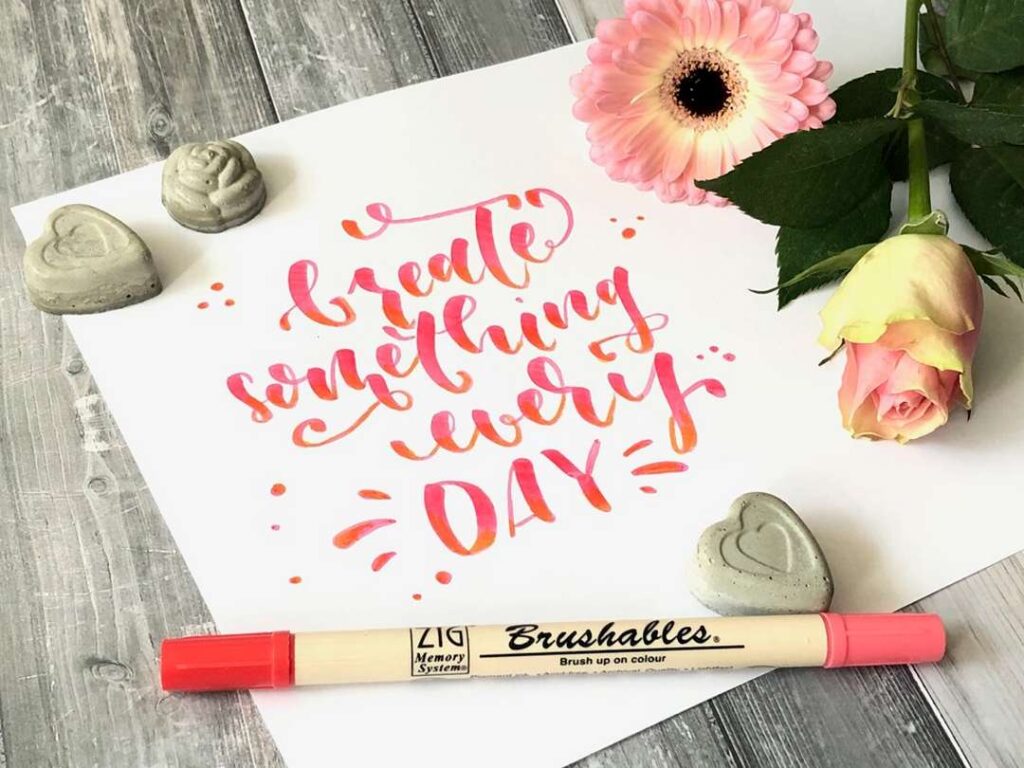
Eksperymentuj z narzędziami
Gdy opanujesz już jedną technikę, zacznij eksperymentować z innymi technikami. Np. do oszukanej kaligrafii wystarczy ci zwykły cienkopis. Spodobał ci się brush lettering – spróbuj pracy z brush penami. Podziwiasz wielokolorowe litery- spróbuj blendingu.
Zbieraj swoje prace i monitoruj postępy
Stwórz swoje portfolio, w którym będziesz przechowywać i dokumentować swoje prace. Warto na pracach zapisywać daty. To pomoże ci w śledzeniu postępów i porównaniu, jak się rozwijasz. Dlatego nie bądź krytyczna do swoich prac. Czasami po odłożeniu pracy, i ponownym spojrzeniu na nią spodoba ci się ona bardziej.